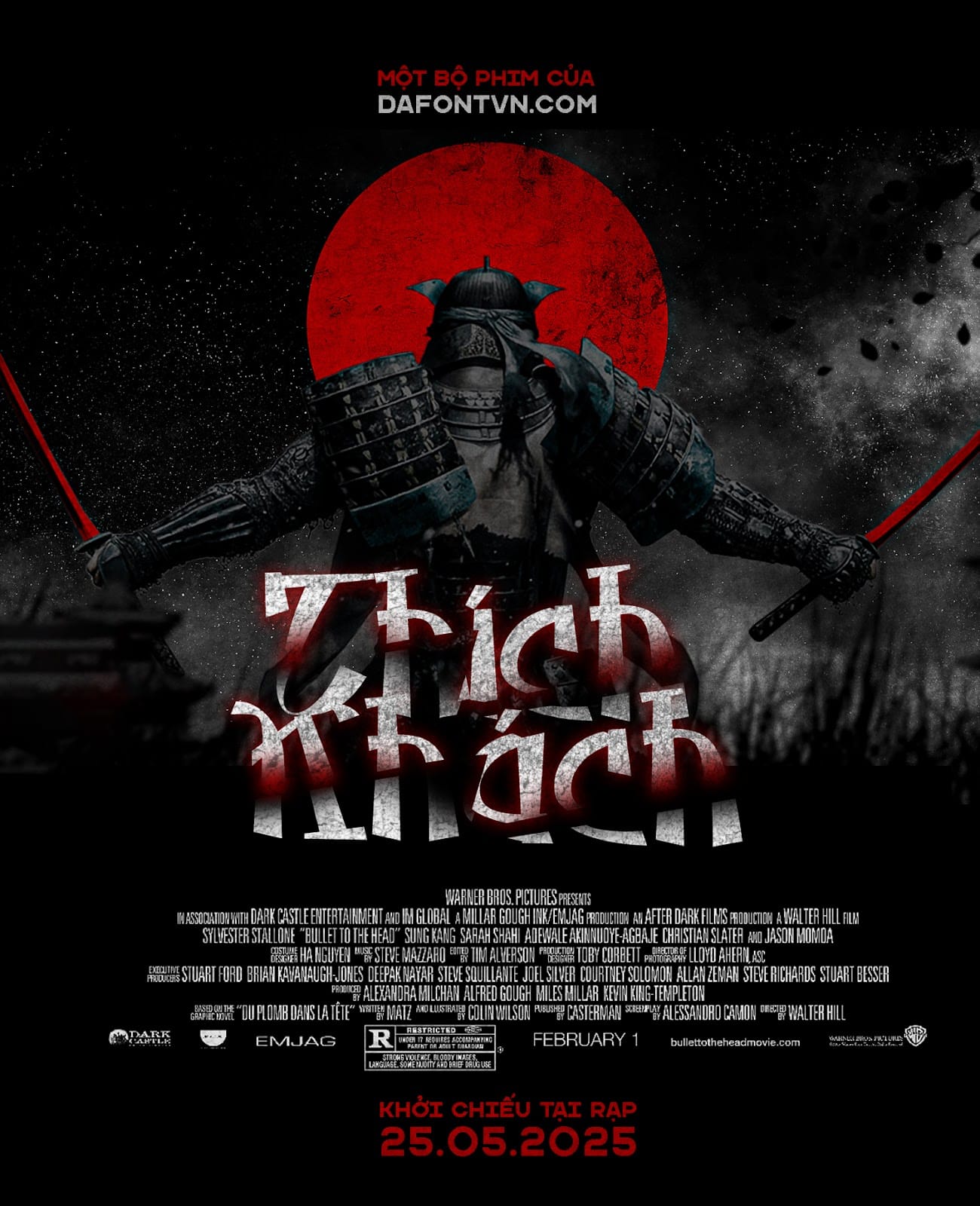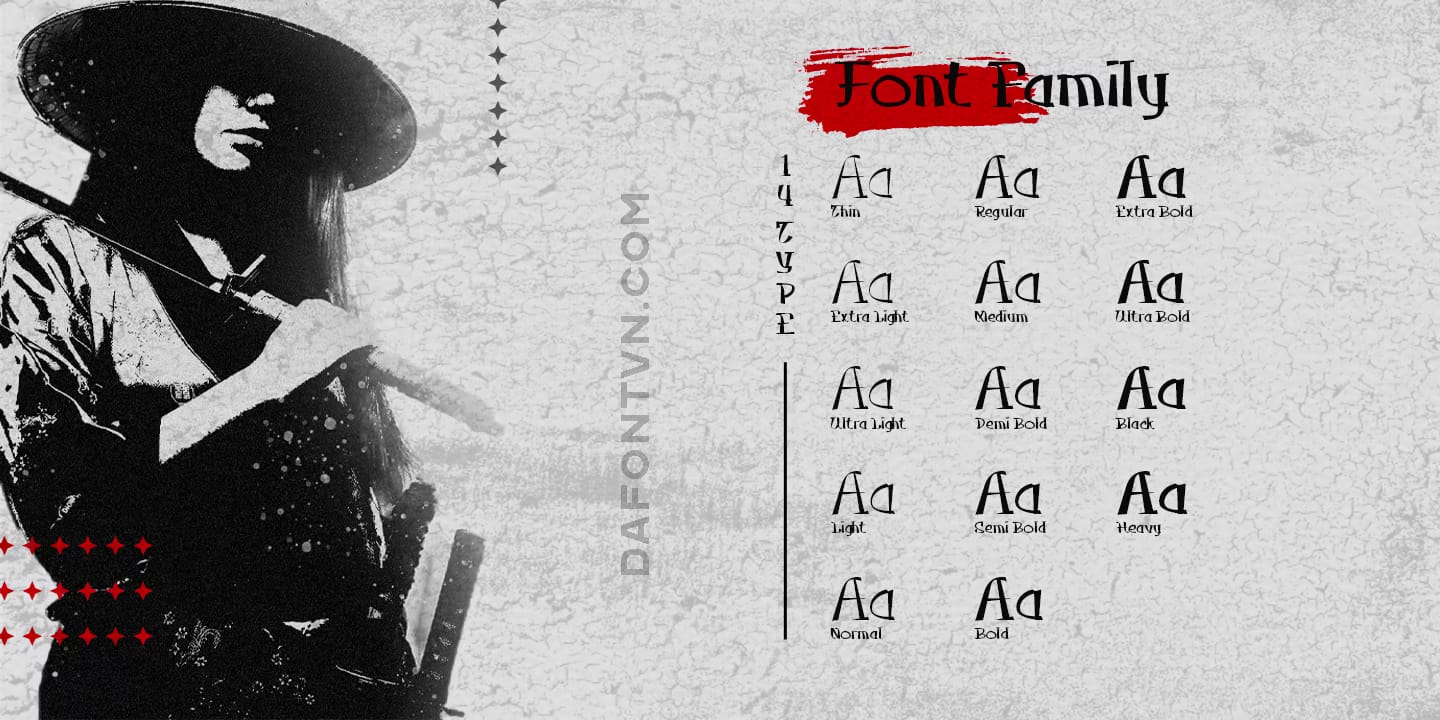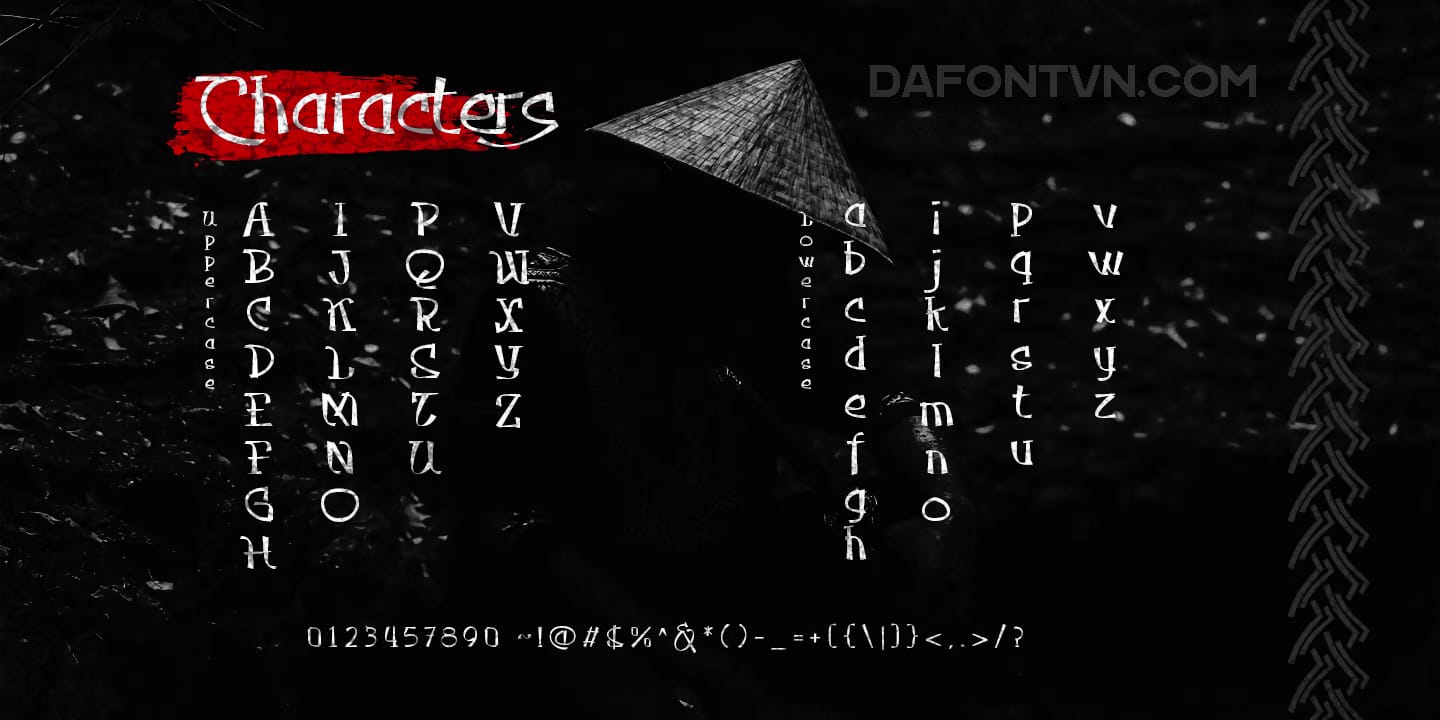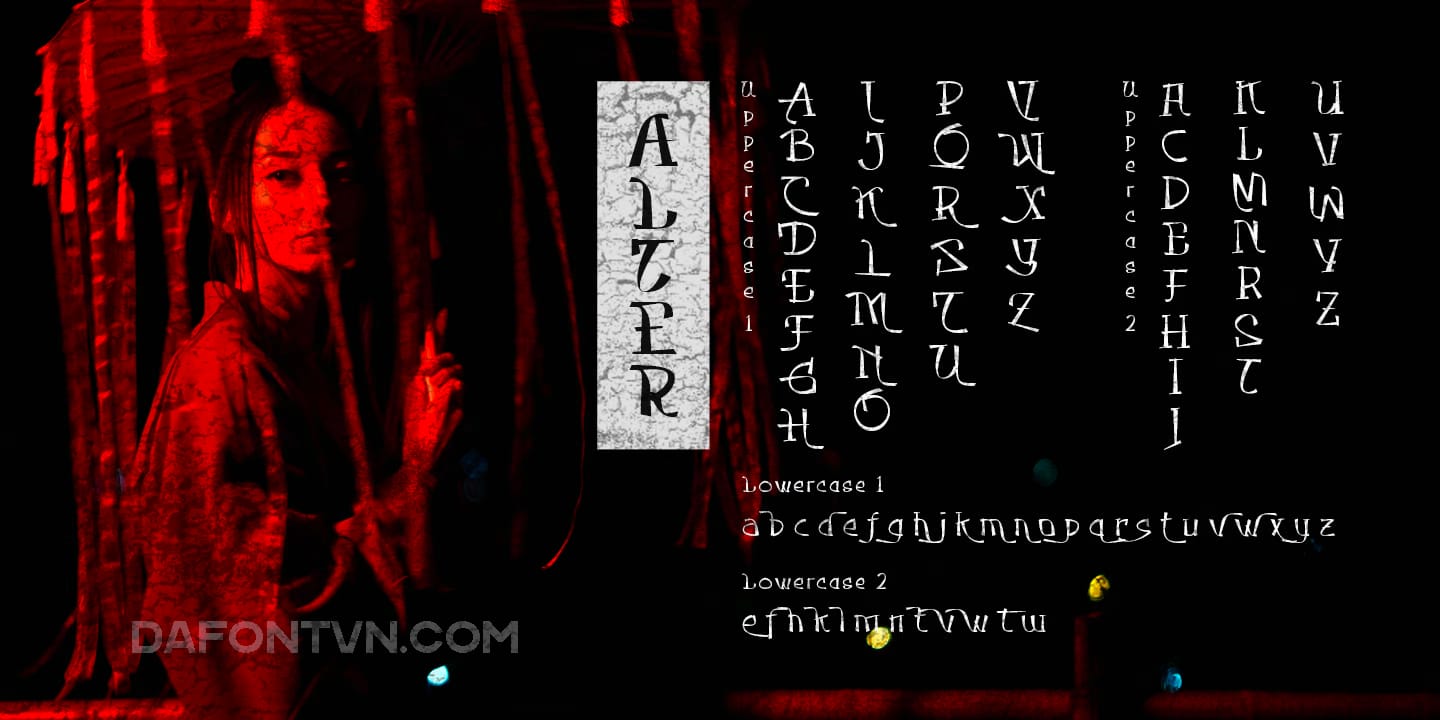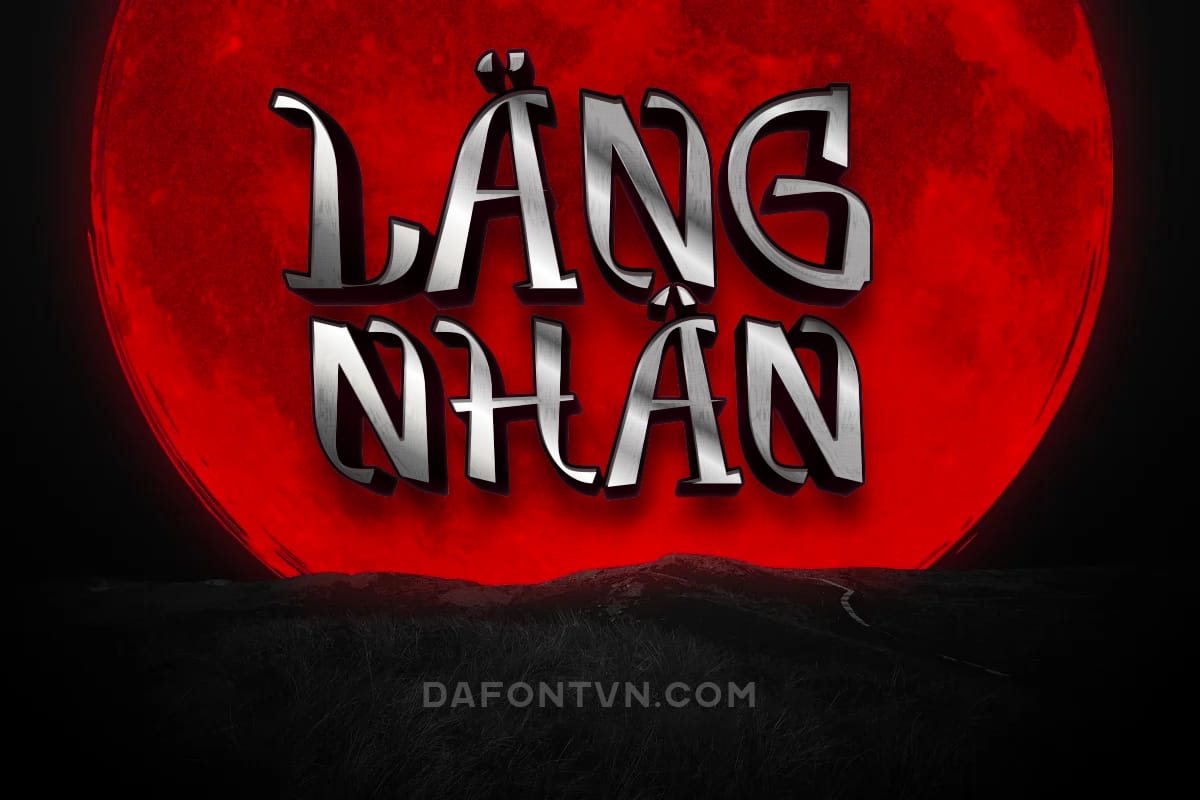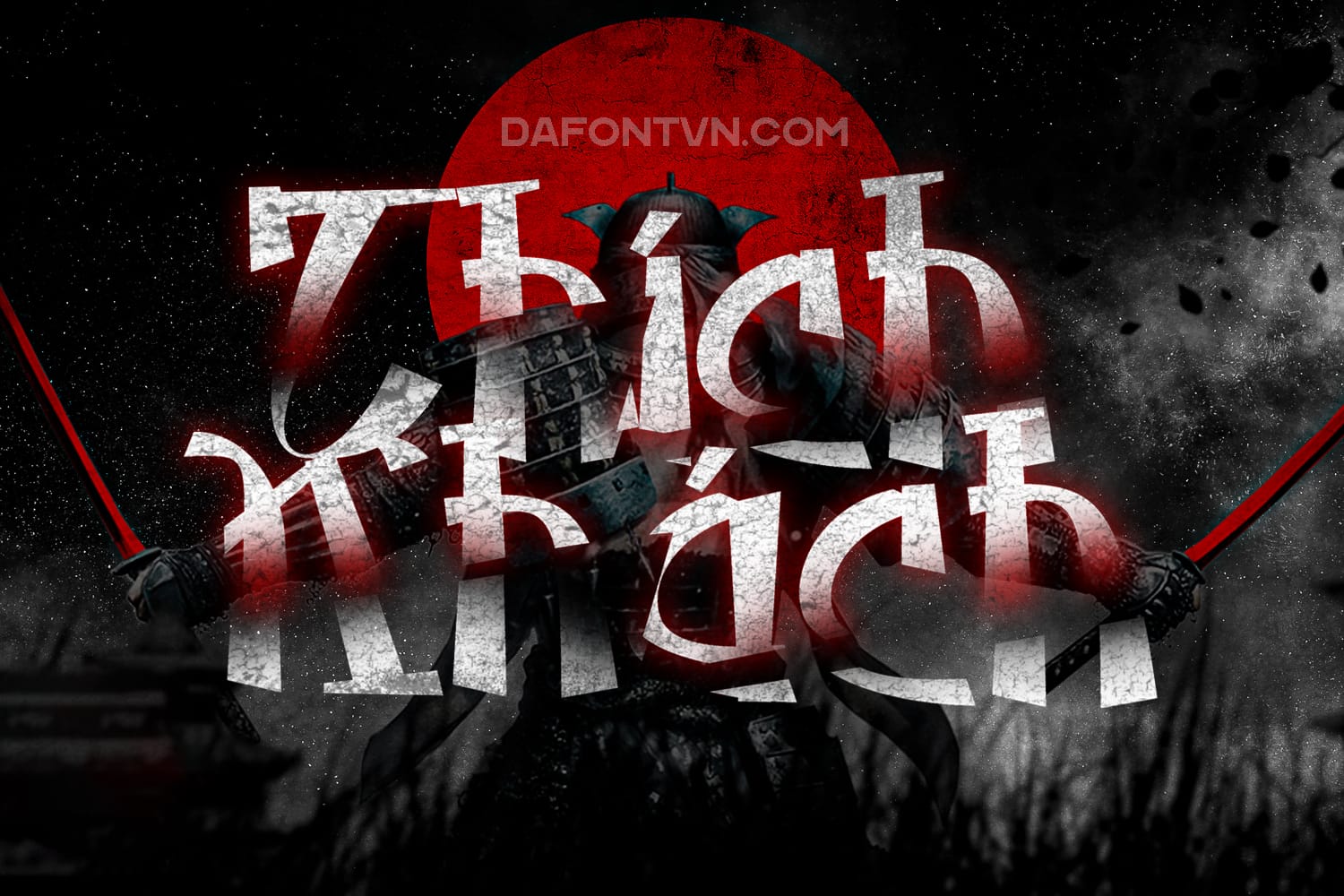
Takashimura font được lấy cảm hứng từ những bức thư pháp độc đáo và thú vị của Nhật Bản, chính vì vậy font chữ này rất phù hợp cho các thiết kế mang hơi hướng Nhật Bản, Châu Á và phương Đông. Ngoài ra, bộ font Takashimura việt hóa này rất dễ sử dụng trong hầu hết các phần mềm thiết kế vì tất cả các alternate và glyph đều được hỗ trợ bởi Unicode (PUA).Font Takashimura với 14 kiểu từ Thin đến Heavy, để sử dụng được những kiểu chữ thay thế bạn cần một chương trình hỗ trợ tính năng OpenType như Illustrator, Photoshop, Indesign…